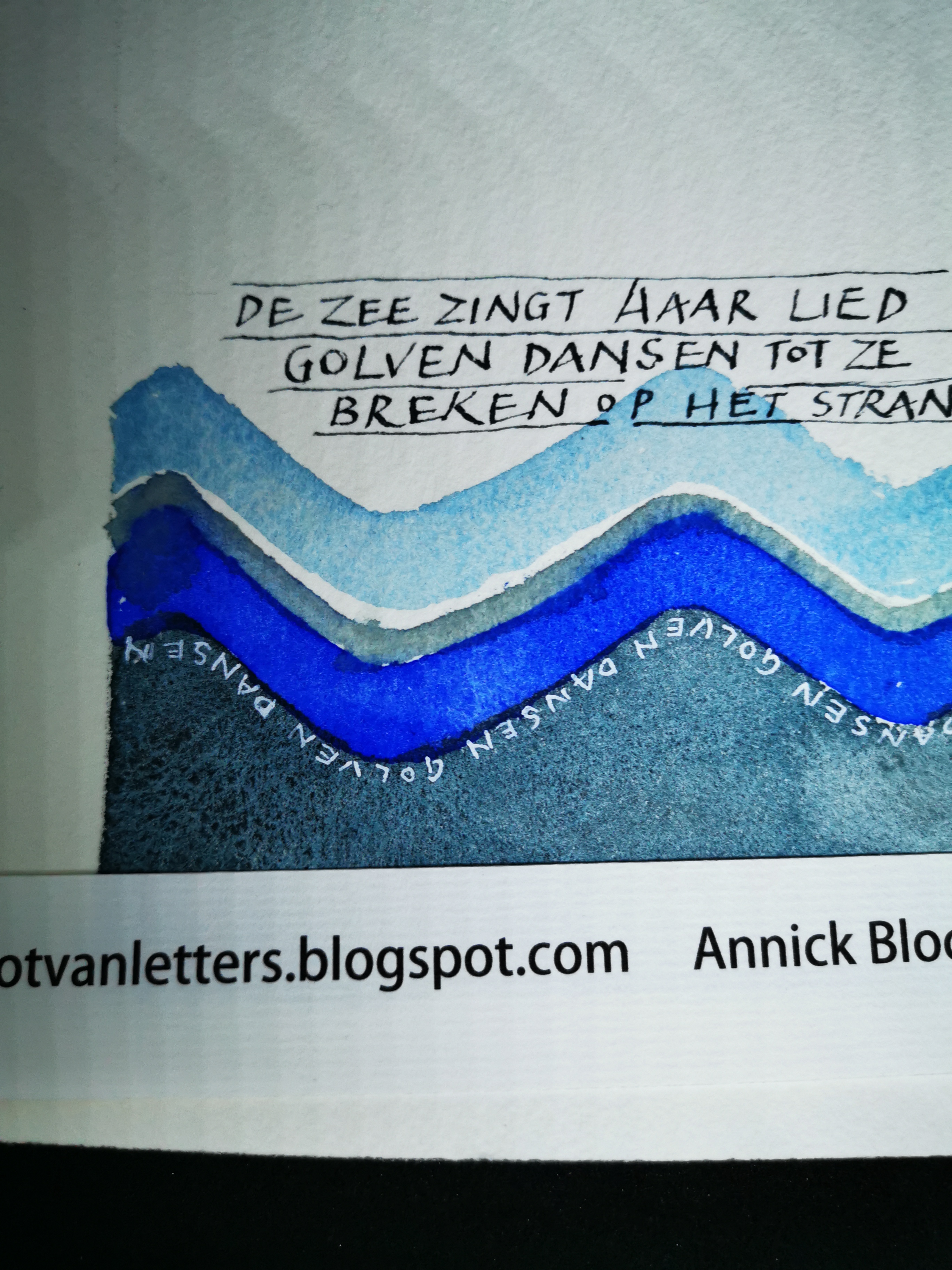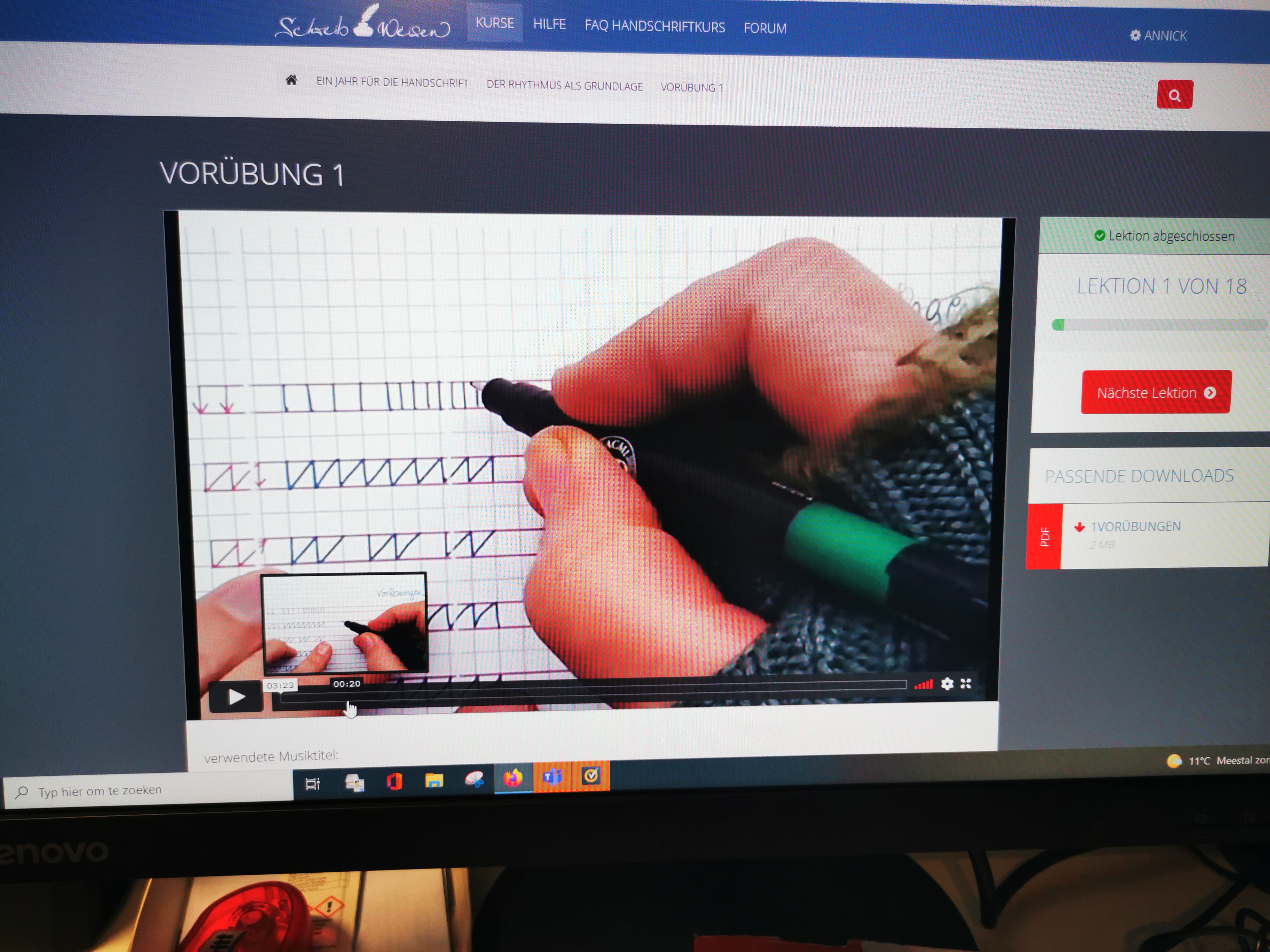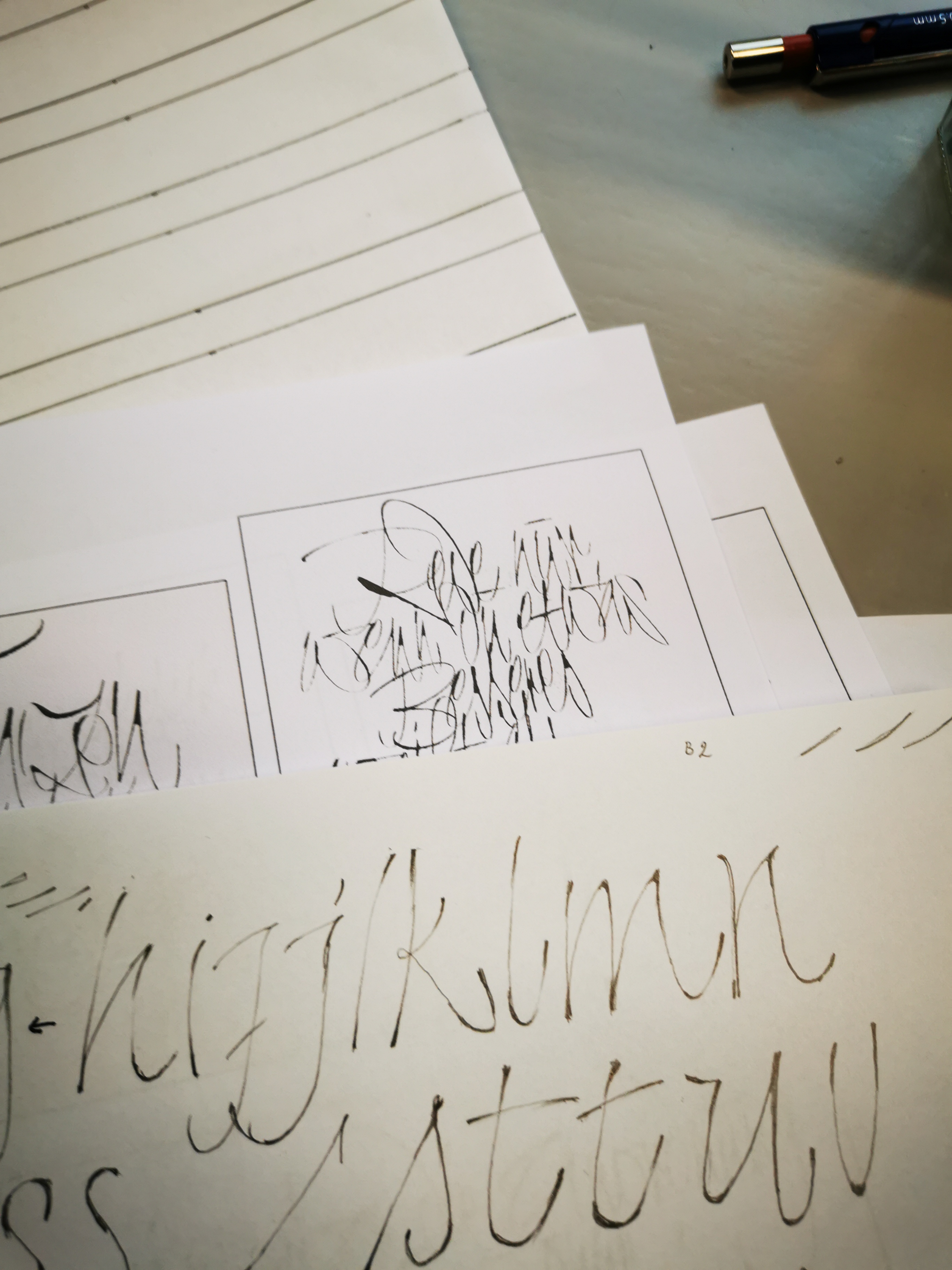
Een tante en nonkel waren onlangs 50 jaar getrouwd !
En dat verdient weer een specialleke, niet ?
My aunt and uncle have been married for 50 years ! So I made them a special card.
Voor de tweede maand van het album-projekt koos Sabine het thema "zee". Ik gebruikte blauwe aquarelverf voor het water en de tekst. Het is een gedicht van Paula Hagemann:
De zee zingt haar lied the sea sings its song
golven dansen waves are dancing
tot ze breken op het strand till they are broken on the beach
The second theme of the year was chosen by Sabine: sea. I used blue watercolour paint for the waves and the text. It's a poem by ¨Paula Hagemann.
Ook volg ik een heel jaar lang de zoom-cursus 'Ein Jahr für die Handschrift' bij Gertrud Ziegelmeir en daar moeten we regelmatig voor oefenen- soms ook op muziek. Hopelijk kan ik hiermee mijn (eigen) handschrift verbeteren. Zal dus maar even gaan oefenen voor de tweede les begint volgende woensdag..
I'm also taking a year-long zoom course with Gertrud Ziegelmeir, called ' a year for the handwriting'. The idea is to improve your own handwriting, so now and then I need to practise, since the second class will be next week.